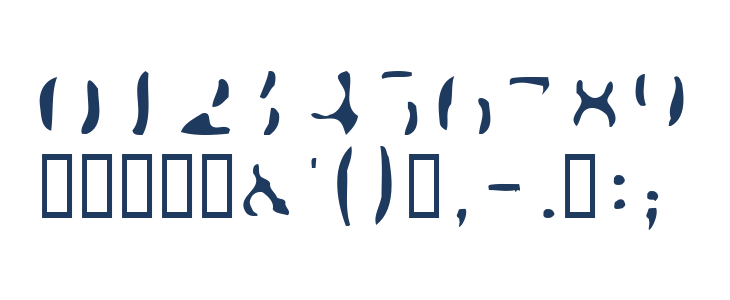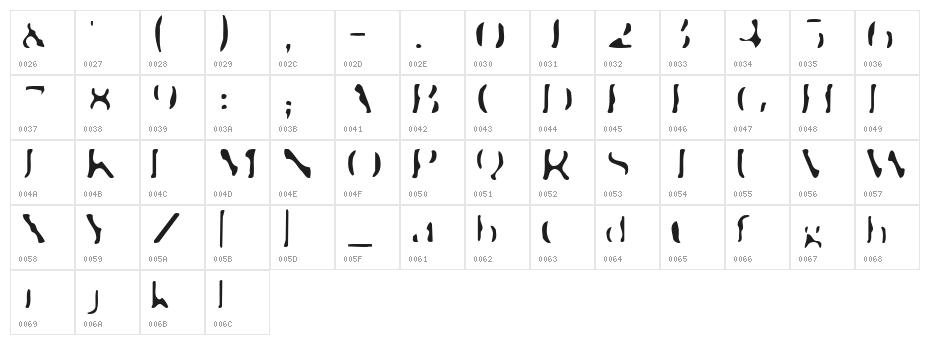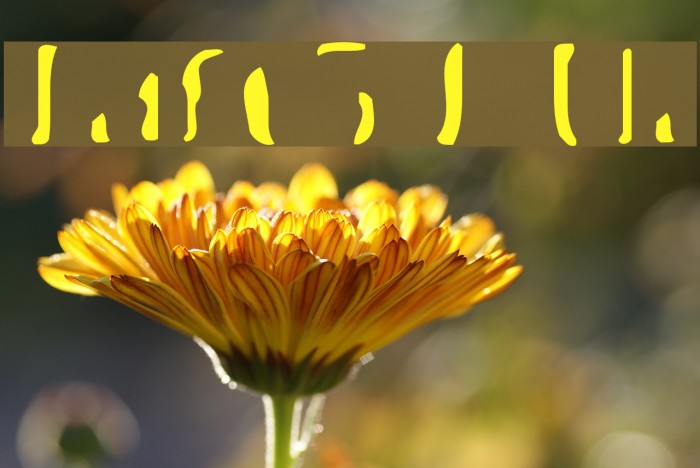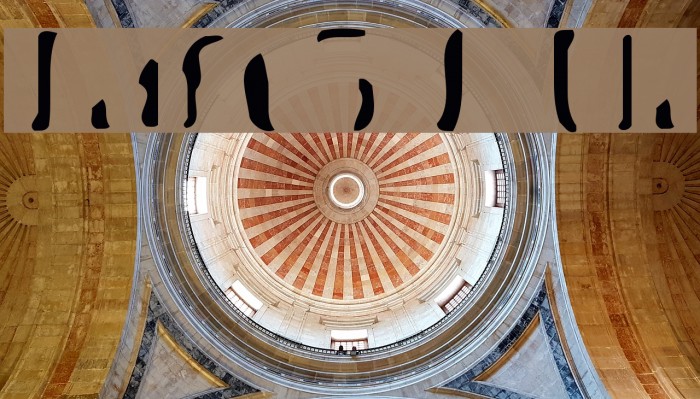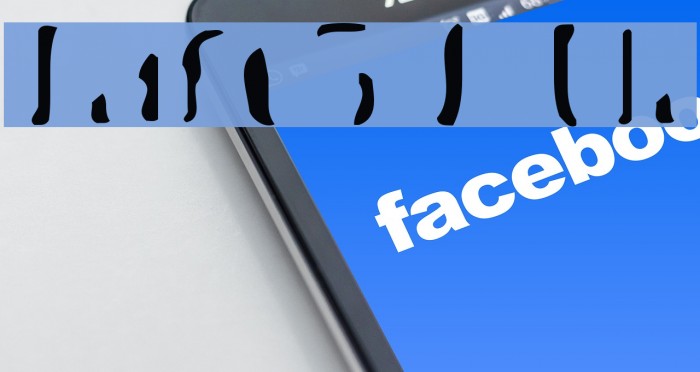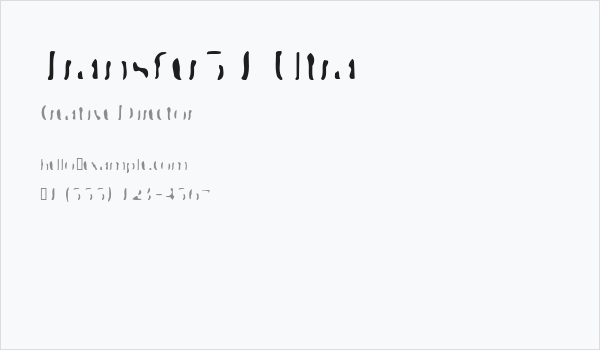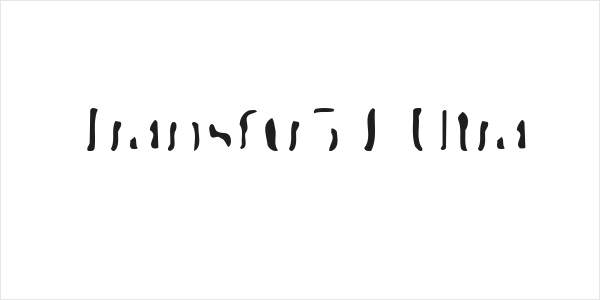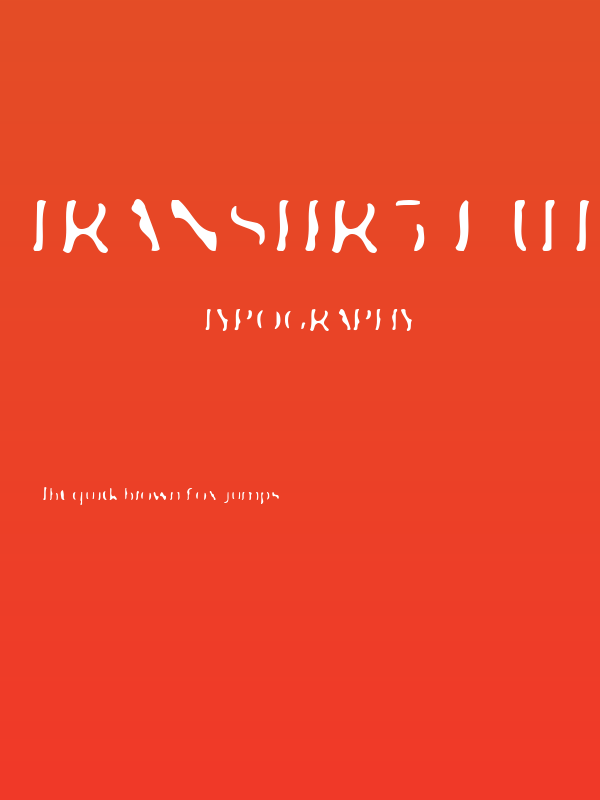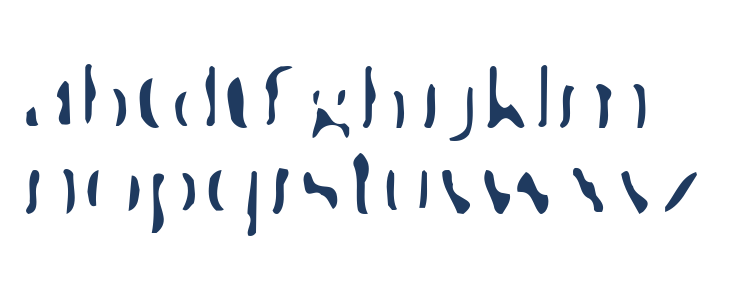
Transfer51 Ultra Font
| Nom | Transfer51 Ultra |
| Poids | Ultra |
| Cas d'utilisation | Logos, Posters, Album Covers |
| Projets proposés | Ideal for creative projects such as posters, album covers, and branding materials that require a distinctive and modern look. |